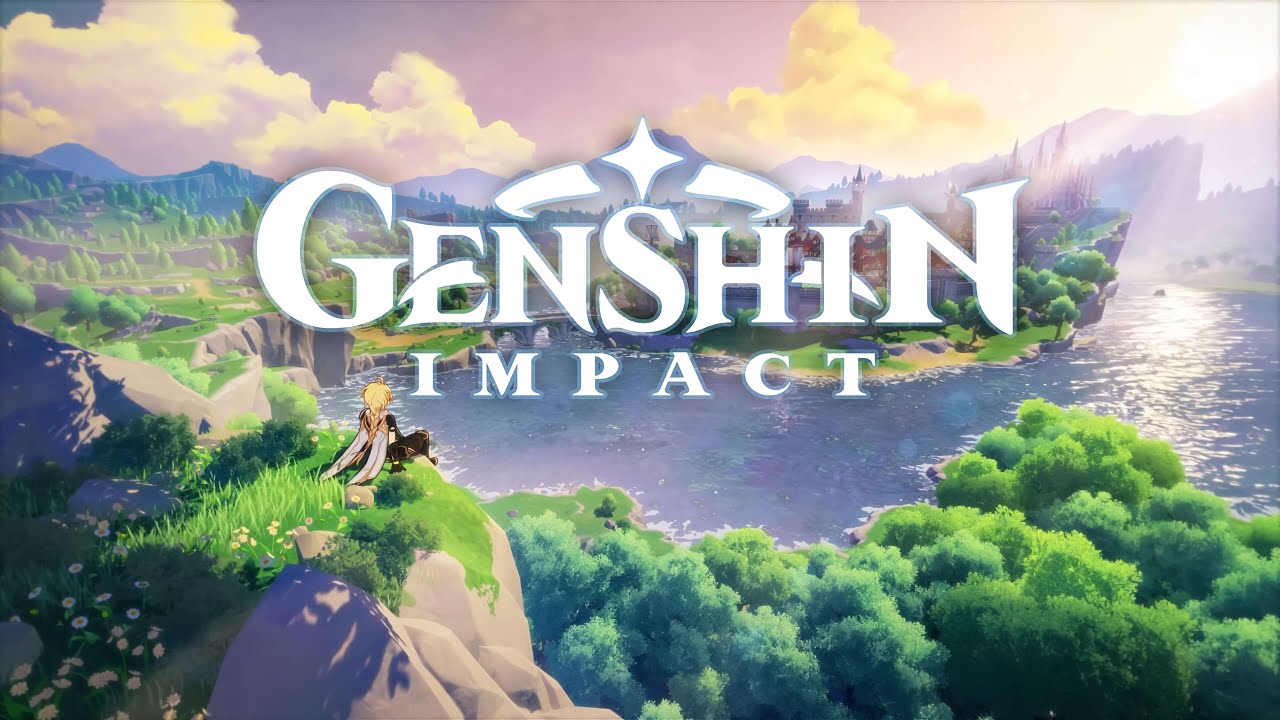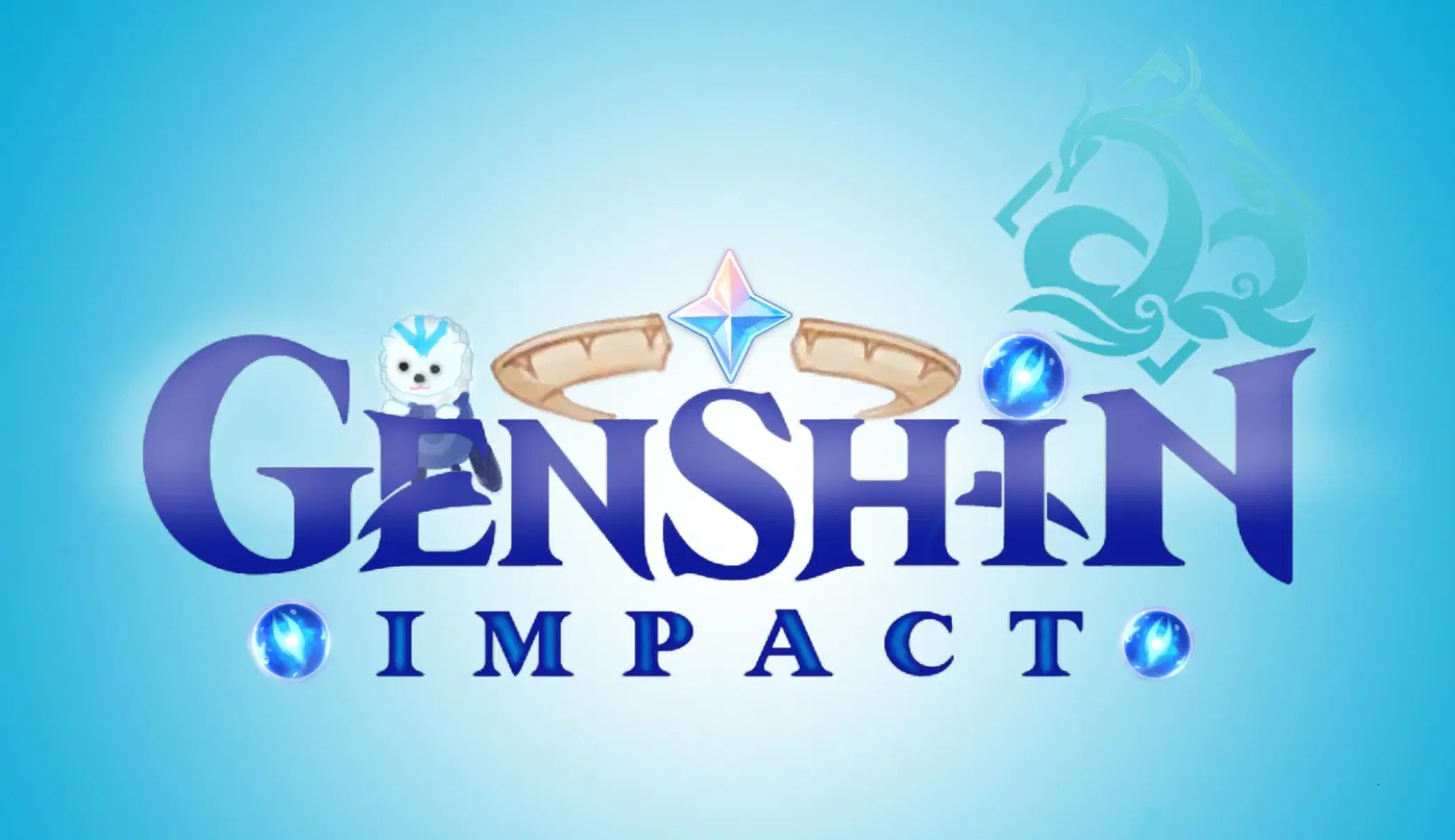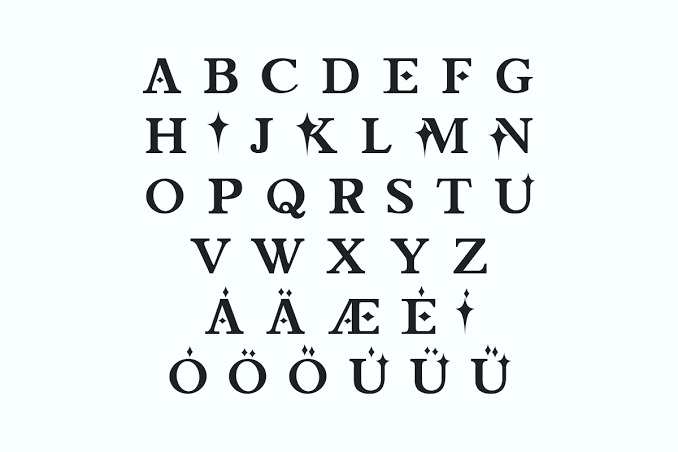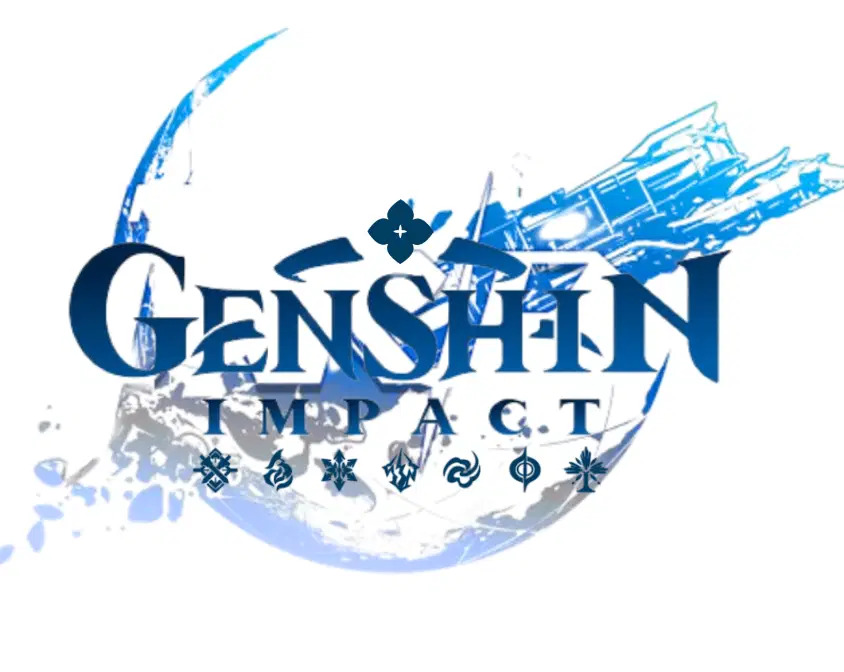
Genshin Impact font Việt hóa là bộ phông chữ giao diện gắn liền với tựa game nhập vai thế giới mở nổi tiếng toàn cầu, nổi bật với cấu trúc Sans-serif hiện đại, các góc bo nhẹ nhàng và khả năng hiển thị rõ nét trên đa dạng kích thước màn hình. Với phong cách thanh lịch, đậm chất công nghệ kết hợp cùng hơi thở phiêu lưu kỳ ảo, font Genshin Impact Việt hóa là chất liệu trực quan tuyệt vời để các kiến trúc sư, nhà thiết kế kiến tạo không gian cho các quán cà phê game thủ container, phòng giải trí eSports trong nhà lắp ghép hay các sự kiện văn hóa giới trẻ.
Tinh thần phiêu lưu Teyvat và độ rõ nét giao diện của Genshin Impact font Việt hóa
Điểm cuốn hút của Genshin Impact font Việt hóa nằm ở sự kết hợp hài hòa giữa tính kỷ luật của phông chữ không chân và sự mềm mại ở các đường bo góc tinh tế, mô phỏng sinh động các khung thoại và bảng chỉ số nhân vật trong game. Cấu trúc ký tự sở hữu độ mở thông thoáng, chiều cao x-height cân đối giúp người xem tiếp nhận các đoạn văn bản dài một cách thoải mái mà không bị mỏi mắt.
Sự ổn định về mặt thị giác của dòng font này tạo nên cảm giác hiện đại, năng động và khơi gợi trí tưởng tượng về những vùng đất giả tưởng rộng lớn. Khi kết hợp cùng các vật liệu kiến trúc hiện đại như vách tôn sóng container sơn màu xanh lam dạ quang, vách kính cường lực dán decal đồ họa, đèn LED dây RGB đổi màu hay sàn gỗ công nghiệp sáng màu, phông chữ Genshin Impact tạo nên sự hòa quyện thẩm mỹ vô cùng ăn ý.
| Phân loại phong cách | Gaming UI / Humanist Sans-serif / Modern Fantasy |
| Mục đích phù hợp | Giao diện game, biển hiệu quán cafe net, poster cosplay |
Tư vấn từ chuyên viên: Genshin Impact font sở hữu đặc tính tối ưu cho việc đọc thông tin nhanh. Để bản thiết kế đạt hiệu quả thẩm mỹ tốt, bạn nên sử dụng phông chữ này cho các tiêu đề phụ, bảng thông số kỹ thuật hoặc menu đồ uống.
03 Ứng dụng font Genshin Impact vào không gian công trình
Nhờ diện mạo công nghệ và tính kết nối mạnh mẽ với cộng đồng giới trẻ, bộ phông chữ này mang lại giá trị thực tế lớn trong khâu hoàn thiện các công trình giải trí hiện đại:
- Hệ thống biển hiệu cho Quán Cafe eSports và Phòng Game Container: Những nét chữ thanh thoát của Genshin Impact rất ăn ý khi gia công chữ nổi bằng mica gắn đèn LED hắt sáng trên nền vách kim loại, mang lại diện mạo thời thượng và thu hút các bạn trẻ ghé thăm giao lưu.
- Trang trí không gian phòng Streamer và Góc giải trí Gia đình: Phông chữ này khi in trên các tấm alu phẳng hoặc dán decal kính sẽ giúp không gian phòng ngủ trong nhà lắp ghép toát lên chất công nghệ, tạo cảm hứng sáng tạo cho người sử dụng.
- Bìa hồ sơ ý tưởng kiến trúc khu phức hợp giới trẻ: Sử dụng font Genshin Impact Việt hóa cho các đề mục thuyết minh dự án giúp ấn phẩm trông hiện đại, tạo thiện cảm với các chủ đầu tư yêu thích sự đổi mới và nhắm đến tệp khách hàng Gen Z.
03 Lưu ý bố cục font Genshin Impact Việt hóa đạt độ tinh gọn và hiện đại
Để khai thác hiệu quả vẻ đẹp của dòng font giao diện game này mà không làm đơn điệu bản vẽ, người thiết kế nên lưu tâm một số kinh nghiệm sau:
- Duy trì khoảng cách dòng chuẩn mực: Cấu trúc chữ của Genshin Impact được thiết kế để xếp khối văn bản rất gọn gàng. Bạn nên duy trì khoảng cách dòng ở mức vừa vặn (khoảng 1.3 – 1.4 lần cỡ chữ) để các khối thông tin giữ được sự liên kết nhịp nhàng.
- Phân cấp thông tin bằng độ đậm nhạt: Hãy tận dụng các biến thể Bold cho các con số số liệu quan trọng và Regular cho phần nội dung mô tả, giúp người xem dễ dàng phân biệt các tầng thông tin mà không cần đổi sang phông chữ khác.
- Lựa chọn gam màu ánh sáng kỳ ảo: Phông chữ phát huy hiệu quả thị giác cao khi phối cùng các tông màu mang sắc thái nguyên tố trong game như xanh ngọc bích, vàng hoàng kim, tím thạch anh hoặc trắng bạc trên nền tối, làm nổi bật đường nét sắc sảo của bộ chữ.